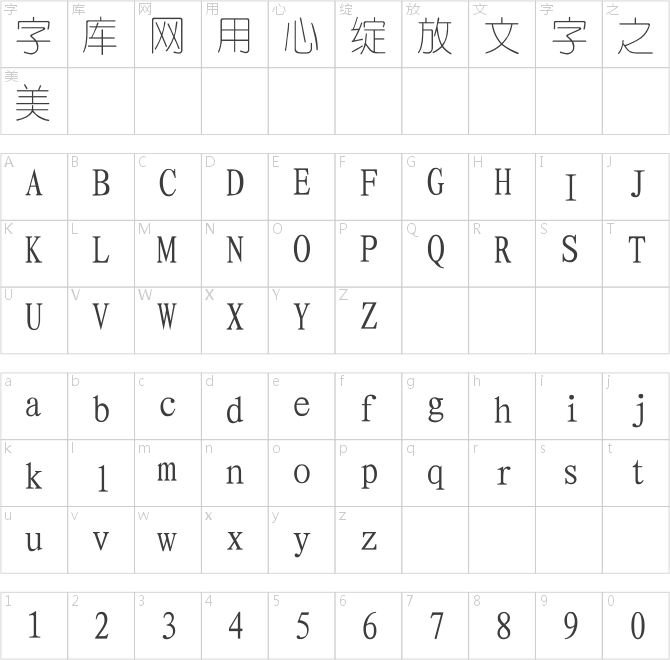
四通利方細(xì)圓體 詳情頁
字體名稱: 四通利方細(xì)圓體
四通利方細(xì)圓體
四通利方細(xì)圓體字體字庫是一款讓人賞心悅目、百看不厭的中文字體,適合各類廣告和產(chǎn)品包裝設(shè)計應(yīng)用,字體大小2.32MB,格式為ttf字體,上傳用戶是凡塵之間,作者/版權(quán)方為未知